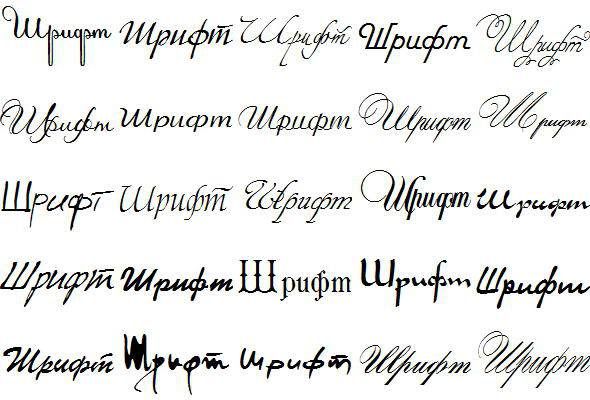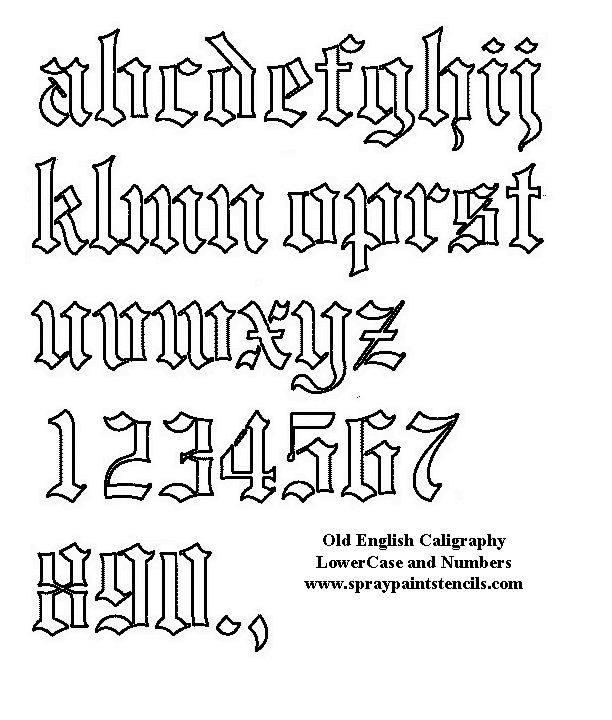
Привет! Меня зовут Егор я практикующий татуировщик родившийся на дальнем востоке, в России.
Я Рисую всю свою жизнь, и работаю татуировщиком. За все время я успел принять участие во
многих интернациональных тату конвенциях, а так же имею опыт в организации конвенций и
выставок для татуировщиков, состою в международной Национальной ассоциации
татуировщиков. Много путешествовал изучая культуру и накопленный опыт других художников и
татуировщиков Азии и центральной России, работал в лучших студиях Пекина, Непала, Москвы и
Дальнего востока России. И сейчас я готов поделится им с вами.
Информация в данном туториале является ознакомительным материалом не только для
мастеров, которые начали свой путь, поняв что эта их профессия, и они готовы посвятить ей
долгие годы своей жизни, но и для тех кто только собирается начать заниматься татуировкой.
Для вас я добавил главу «Basic», где вы найдёте ответы на вопросы относящиеся к подбору
оборудования, подготовки рабочего стола и первых шагов в профессии.
Я много путешествовал и встречал разных людей, которые занимаются татуировкой
определенное время. У них уже есть базовые навыки, и накопленный опыт, своя клиентская база.
Однако они сталкивались с проблемой, перехода на следующую уровень.
В этом материале мы разберём с вами полностью 1 рабочий день : от подготовки, работы с
эскизом, до нанесения татуировки и заживления.
BASIC.
Профессия. Оборудование. Подготовка. Первые шаги.
Если вы уже имеете небольшой опыт работы, уверенно ведёте линии, знаете в какой стилистике
хотите развиваться и умело оперируете базовыми знаниями, то рекомендую перейти сразу на
страницу …
Профессия. Введение.
Татуировщик сегодня, это не только человек, который держит в руках машинку и делает
качественно татуировки, но и человек который разбирается в искусстве фотографии, дизайне, маркетинге, актуальных трендах, психологии, правилах асептики и антисептики.
Безусловно хороший татуировщик = хороший художник. Многие татуировщики пришли в
профессию из художественных профессий и имеют качественную художественную базу навыков и
продолжают совершенствовать их. Если вы хотите делать качественные татуировки, и у вас нет
или недостаточно художественных навыков, то я рекомендую вам начать с изучения основ
композиции, рисунка и колористики или использовать различные курсы, сейчас в интернете есть
колоссальное множество бесплатных каналов по рисунку, которые вы можете просматривать в
свободное время. Это сэкономит для вас много времени в будущем. Ниже я привёл лишь
некоторые примеры каналов на YouTUBE, которые вы можете использовать в получении новых
знаний.
Так же имейте ввиду, что профессия татуировщик, это каждодневный труд, включающий в себя
постоянное разностороннее развитие себя, своих навыков и самообучение.
Оборудование.
Для комфортного старта работы вам необходимо качественное оборудование.
Оно может быть
не самого высокого уровня, но и не должно быть самым дешевым. Не думайте, что сейчас вы
сэкономите, купив готовый тату набор, и возможно у вас что то получится.
Из личного опыта я скажу вам, что вы потратите больше времени с настройкой этого
оборудования. Сейчас на рынке существует множество машинок среднего ценового сегмента, которые позволяют сделать качественный и быстрый старт. Так же вы можете не покупать сразу
всю палитру красок, а ограничиться только базовой палитрой в 7 цветов, белым и чёрным.
Тату машинки. Иглы. Силовое оборудование.
Здесь я рассмотрю 2 классические категории : индукционные и роторные тату машинки. Так же
есть несколько типов комбинированных тату машин , которые используют элементы одних в
других. Ниже кратко разберём ключевые особенности каждой из них.
Индукционные тату машины . Классика – процесс движения иглы производится за счёт
поступательно ударного движения при помощи электромагнита.
В качестве электромагнита здесь
выступают магнитные катушки.
Из плюсов стоит отметить четкое разделение тату машин под разные виды работ : liner – для
линий , shader – для заливок и теней . Для каждого типа работ у вас будет отдельная тату машина.
Хлёсткий удар, за счёт высокой скорости возвратного движения, пигмент лучше вбивается внутрь
кожи и его количество значительно больше, чем это делает роторная татумашинка.
Из минусов, конечно, вибрация и вес , к которому в начале нужно привыкнуть, по началу нужно
будет к этому привыкнуть, могут уставать руки и болеть запястья. Громкий звук и сложность
настроек. Требовательность к вашим навыкам владения татумашинки.
Роторные тату машинки – здесь используется мотор, а не катушки . Движение иглы производится
за счёт преобразование крутящего момента в возвратно-поступательный. В большинстве случаев
Изменения обычно отображаются на введённой ранее фразе.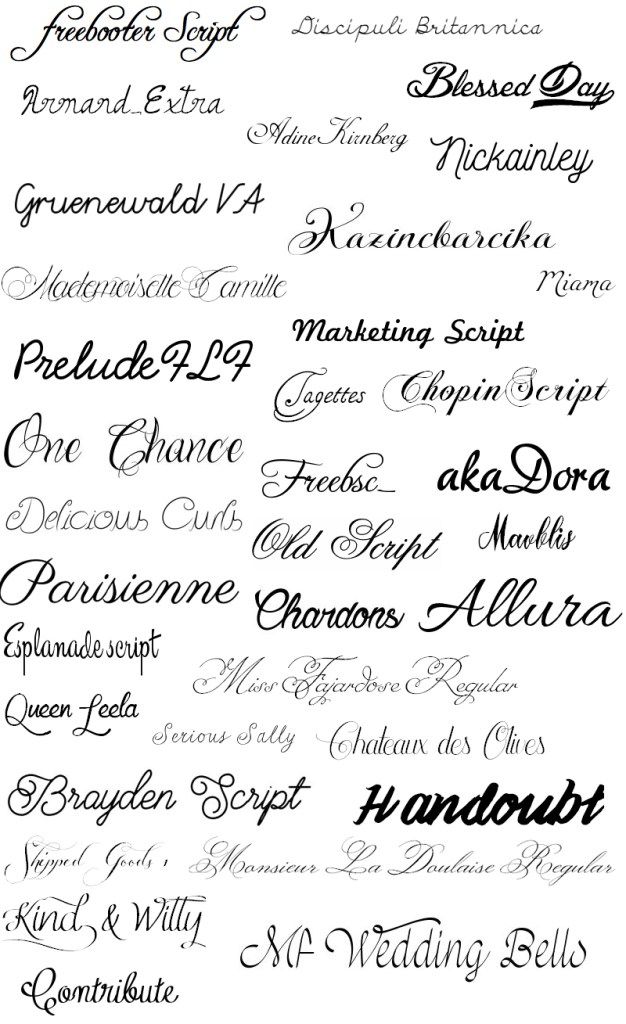
К примеру, суровая жизненная фраза из нежных плавных букв с бабочками и подобным оформлением будет выглядеть слишком необычно. Выбор шрифта также зависит не только от смысла, но и от наполнения тату. Если оно представляет собой пару или больше слов, для них подойдёт один стиль, если же это одно слово, его заглавную букву выделяют отдельно.
Этот способ является капризом клиента, для выразительных фраз на латинском обычно достаточно подобрать соответствующий шрифт.